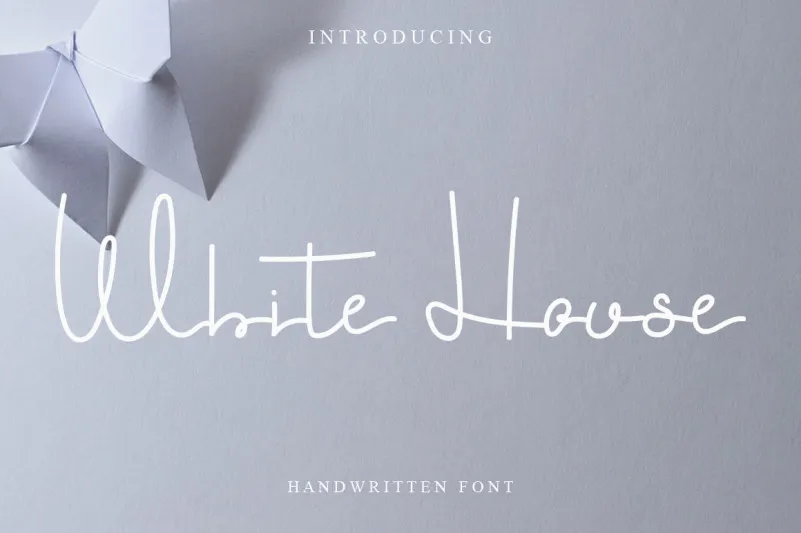
White House Font – Download Grátis
Esta é uma linda fonte escrita à mão cíntica e fina, ideal para aqueles que buscam algo delicado e sofisticado para seus projetos. Com seu ar agradável e elegante, essa fonte será perfeita para adicionar um toque amigável e romântico em qualquer projeto gráfico. Seja ela um slogan no site da sua empresa ou letras de uma história emocionante em sua nova publicação, você certamente encontrará sua usabilidade incrivelmente versátil. Sem dúvida, essa fonte será o complemento perfeito para qualquer design criado pelo designer levincreative.